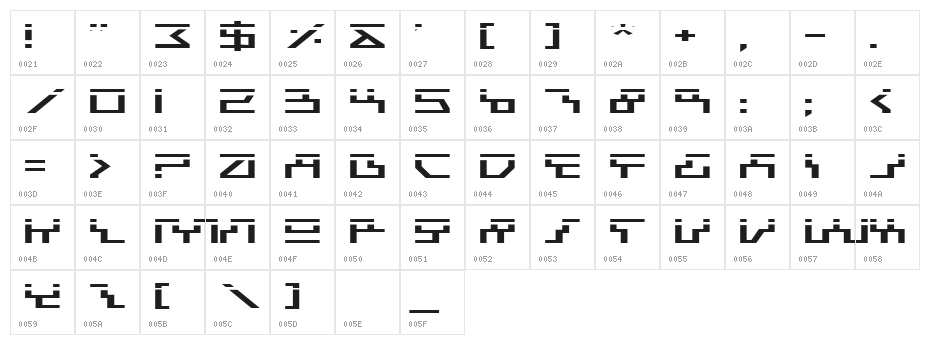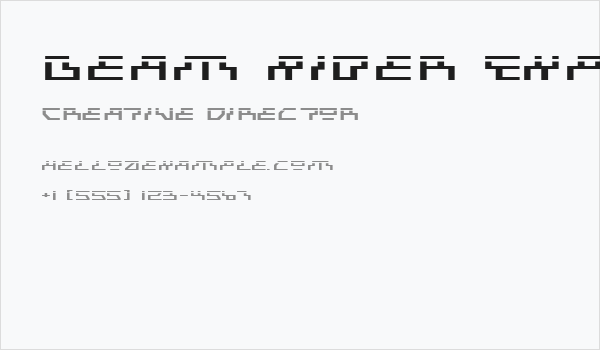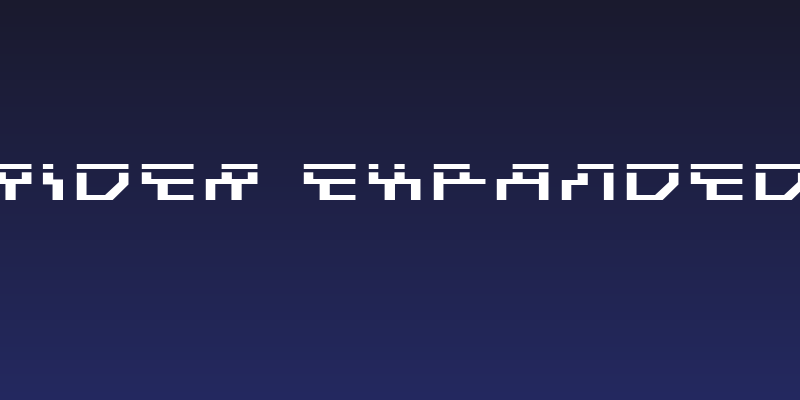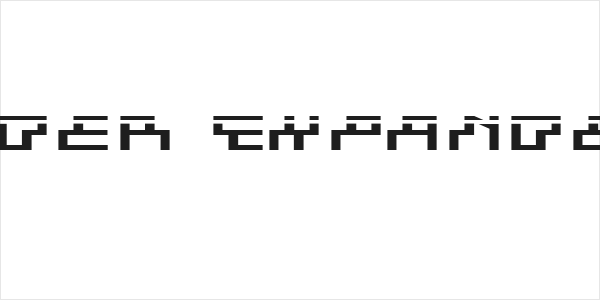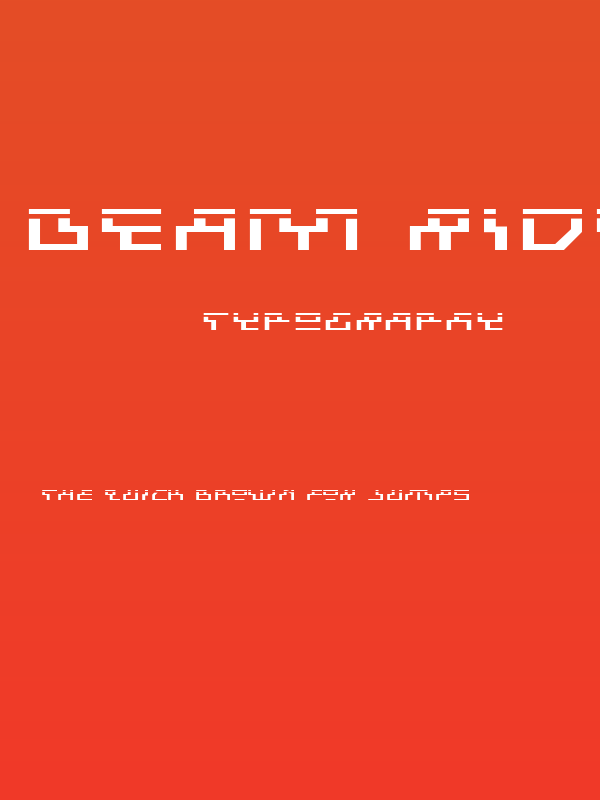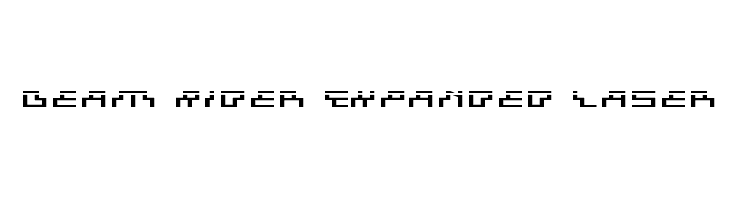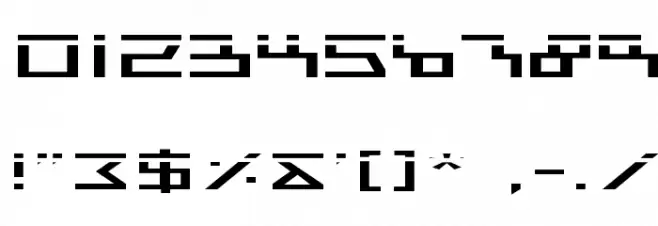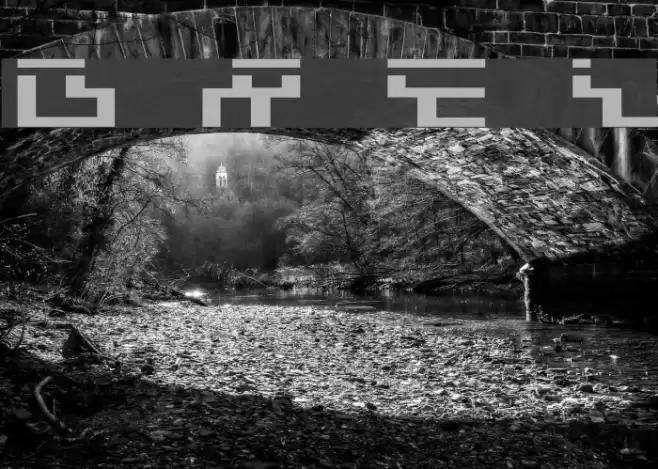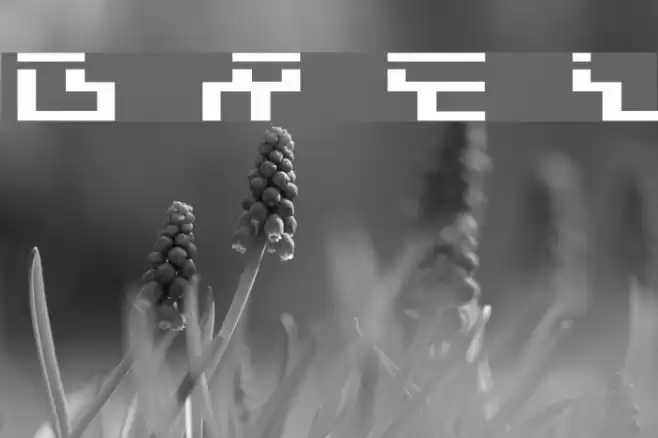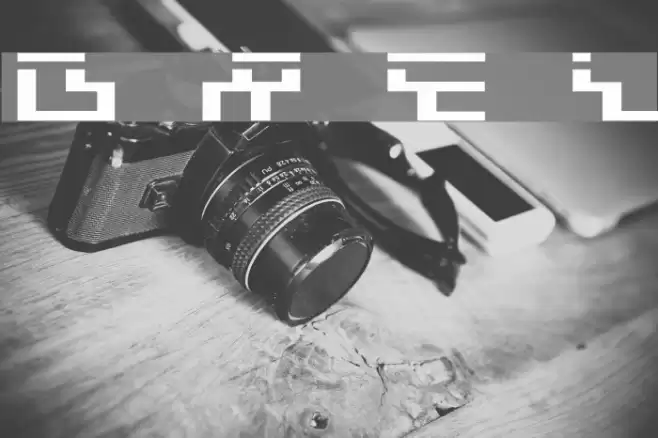
Beam Rider Expanded Laser Font
| Peso | Expanded Laser |
| Categorias | Capitals |
| Largura | Expanded |
| Estilo geral | Futuristic |
| Projetos propostos | Ideal for video game graphics, sci-fi themed posters, tech branding, and digital interfaces. |